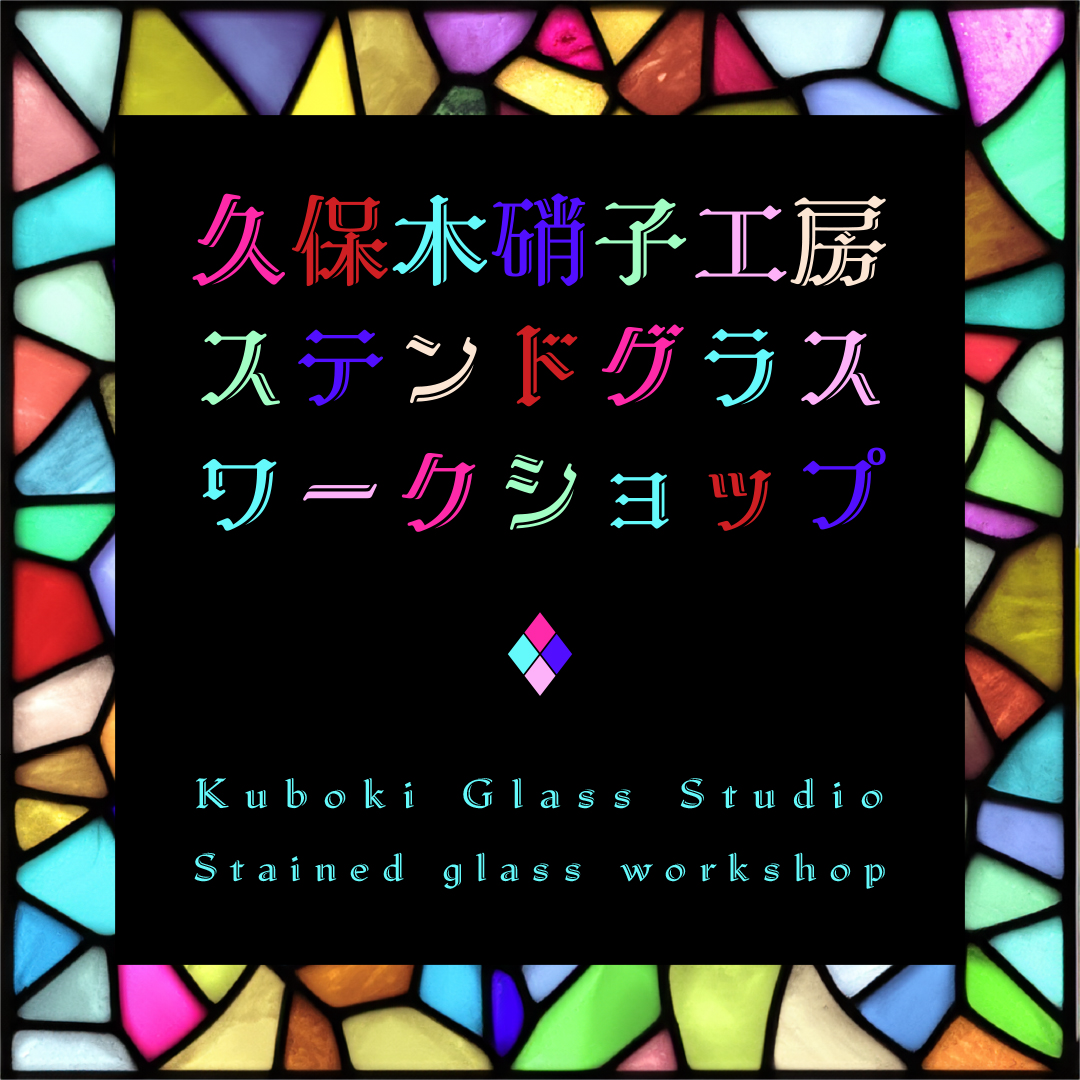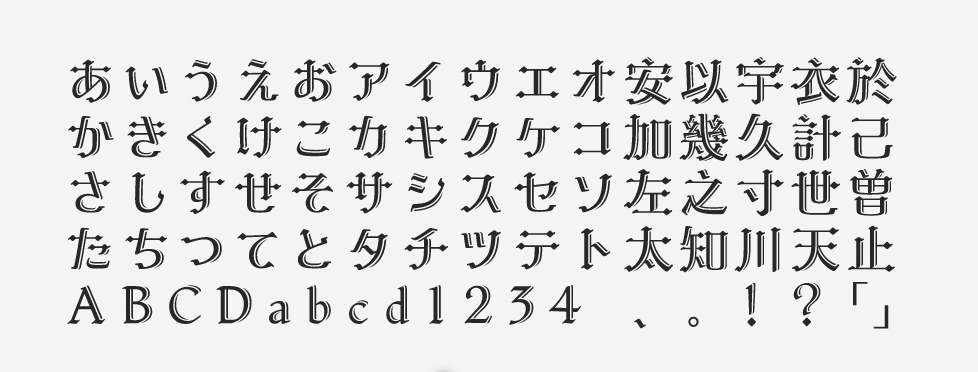
「白のアリス」について
白のアリスは、タイプバンクブランドのかな書体・TBかナ-白のアリスに漢字を追加して完成したフォントです。2022年秋の新書体として提供が開始されました。先行してリリースされていたレトロモダンな赤のアリスにラインを加え、装飾性を高めたフォントです。
「白のアリス」の特徴
平筆に由来する西洋風のストロークや、クリアで柔らかなエレメント・骨格が特徴です。レトロモダンな雰囲気を演出でき、華やかさと可愛らしいイメージを備えています。
ゲームやコミックの表紙、見出しやキャプションなど、表現したい方向性とマッチしていれば、さまざまな場面で活躍するフォントです。赤のアリスと比べると、ラインが追加されていることによって立体感が増しています。
作例はステンドグラスに関するデザインなので、装飾性が高くて奥行き感もある白のアリスはまさにぴったりでした。かなり凝ったフォントで、このようにハマるケースでは重宝されます。唯一無二の存在と言えるでしょう。欧文のデザインも素晴らしいです。